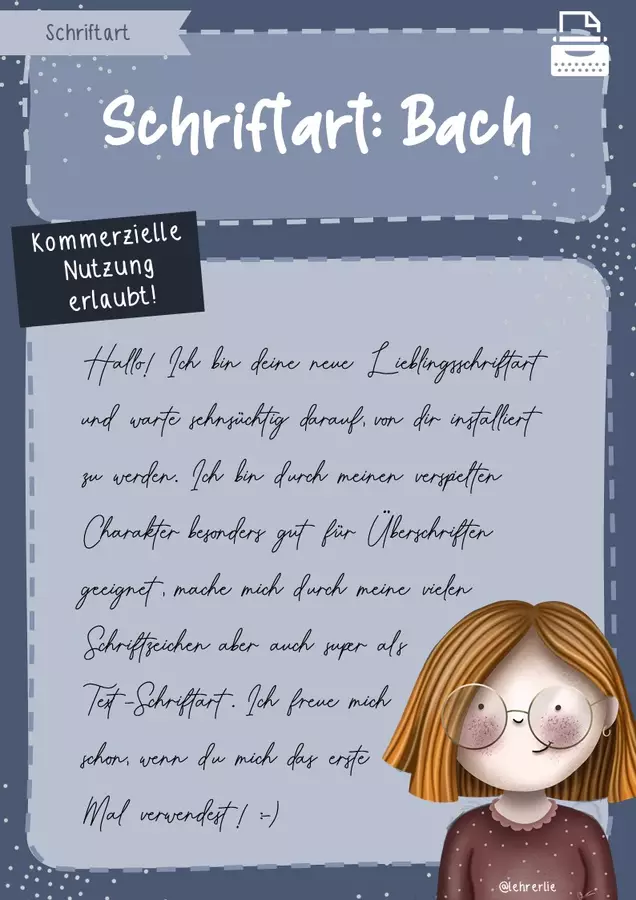
Ich präsentiere: die erste Schriftart aus meiner Komponisten-Reihe. "Bach" ist eine besonders ästhetische und verschnörkelte Handschriftart, die eine ganz normale Überschrift schnell mal wie ein tolles Handlettering aussehen lässt!